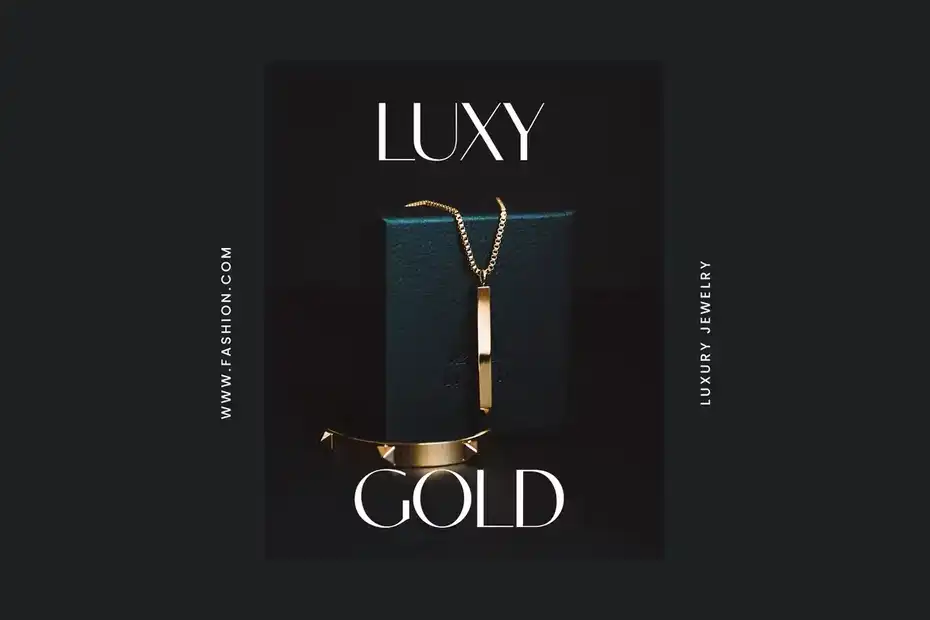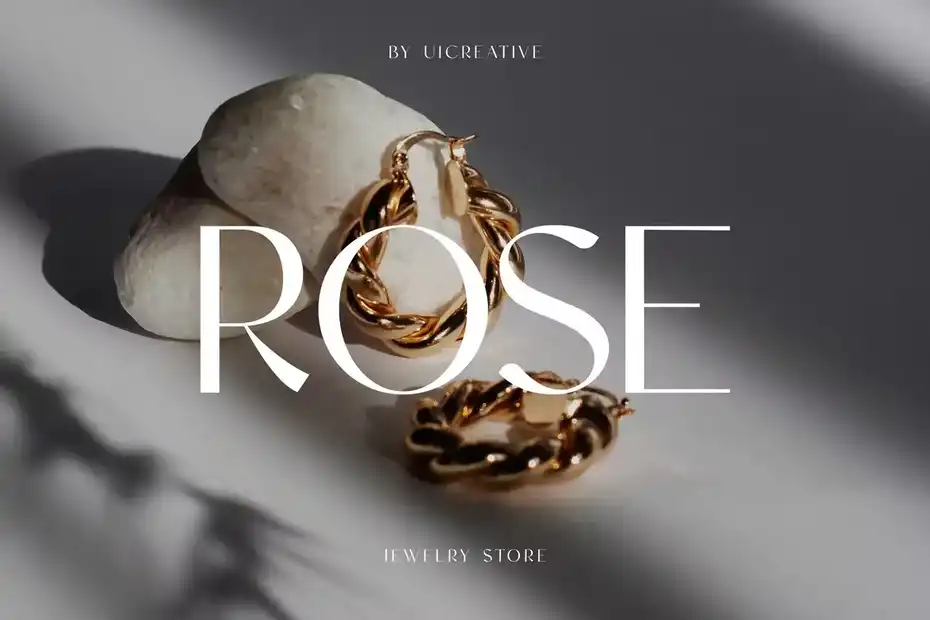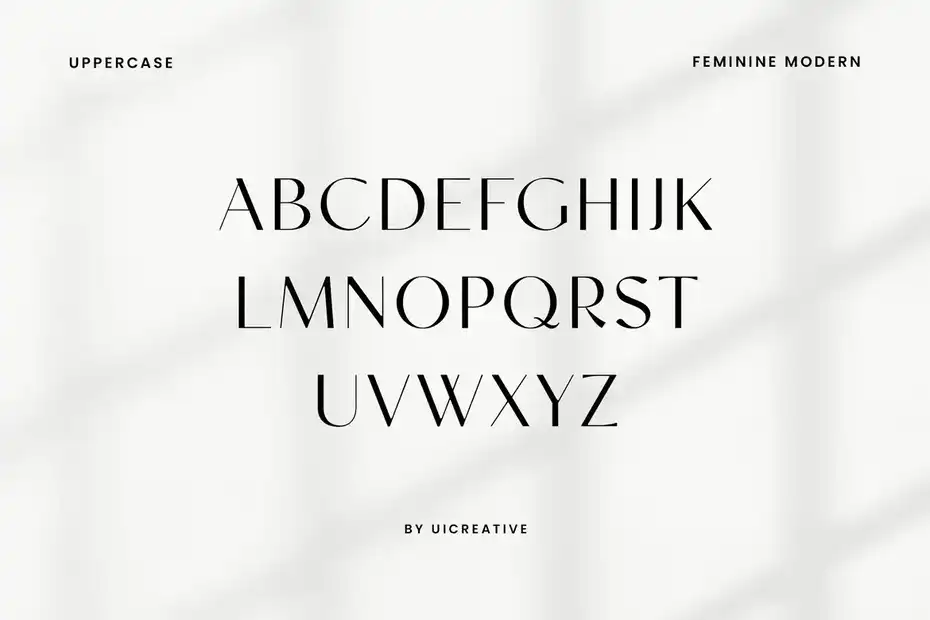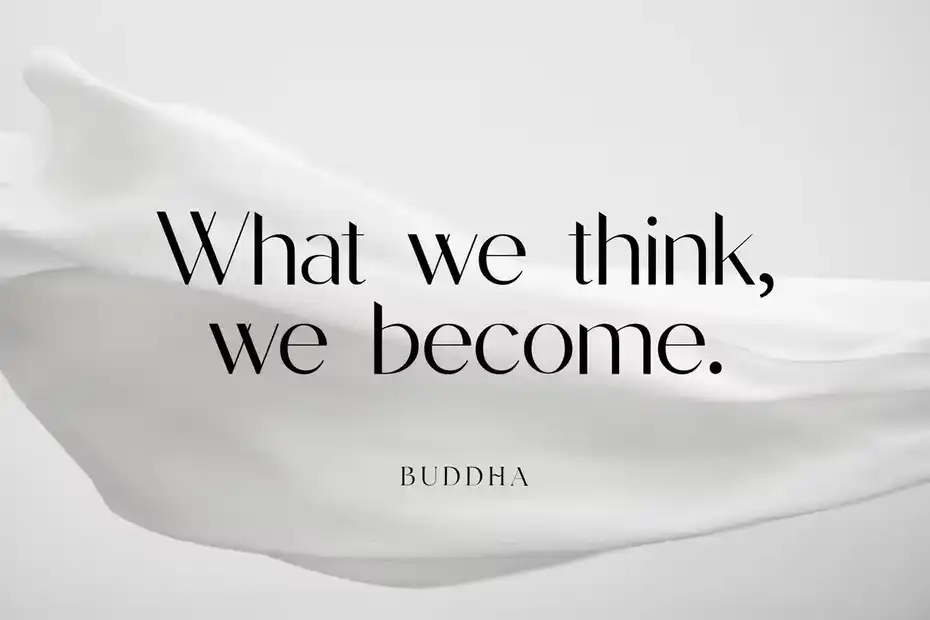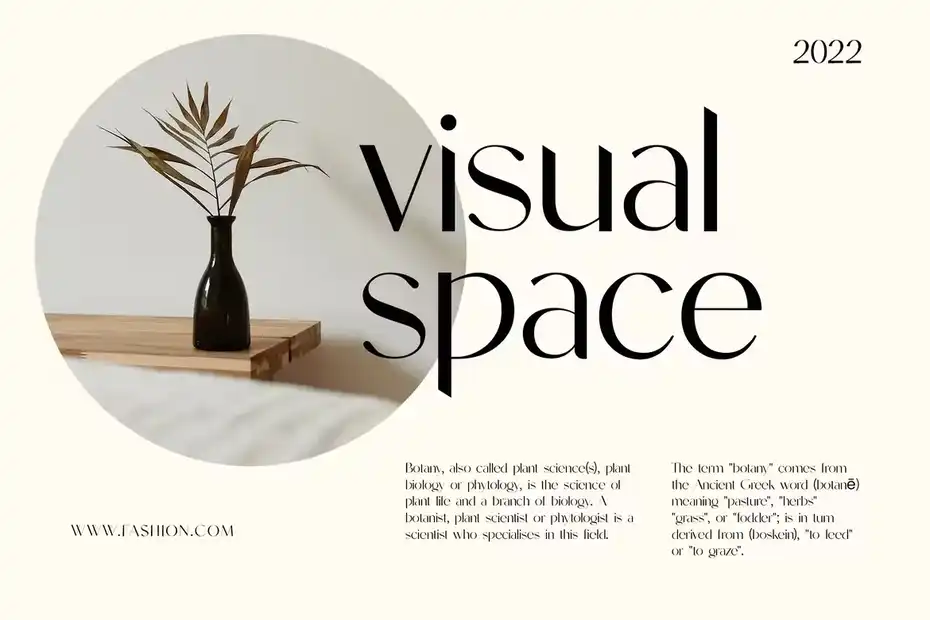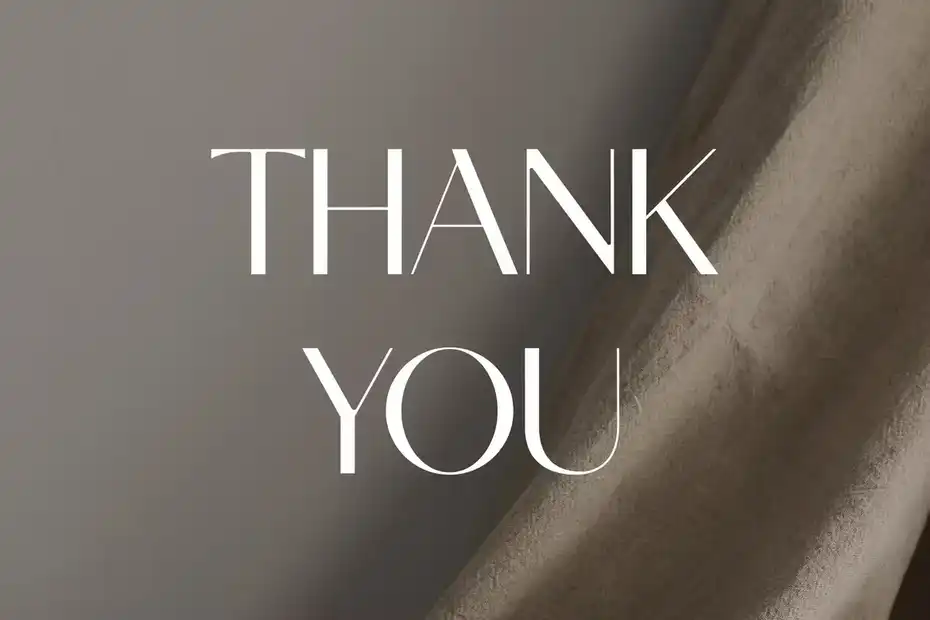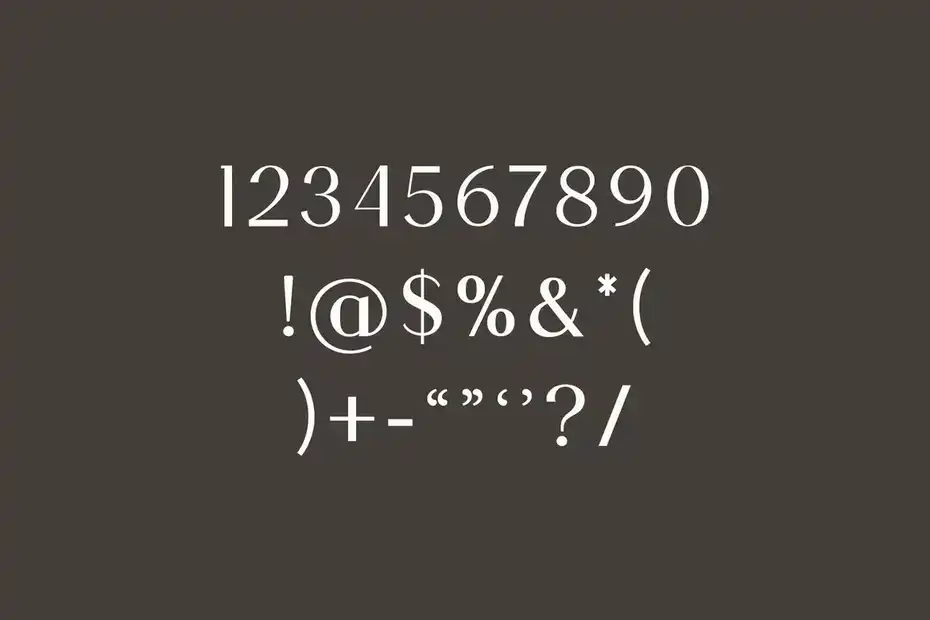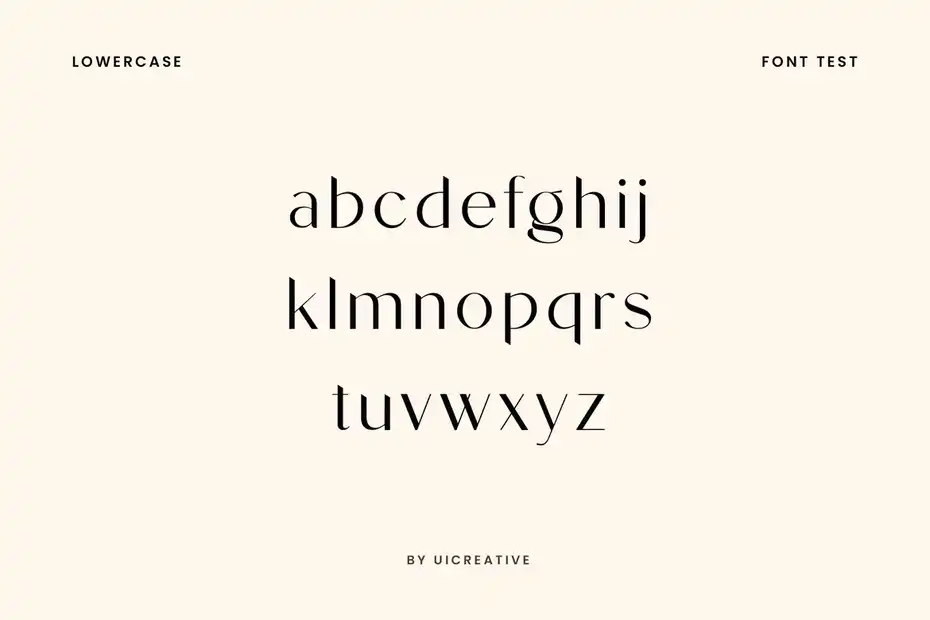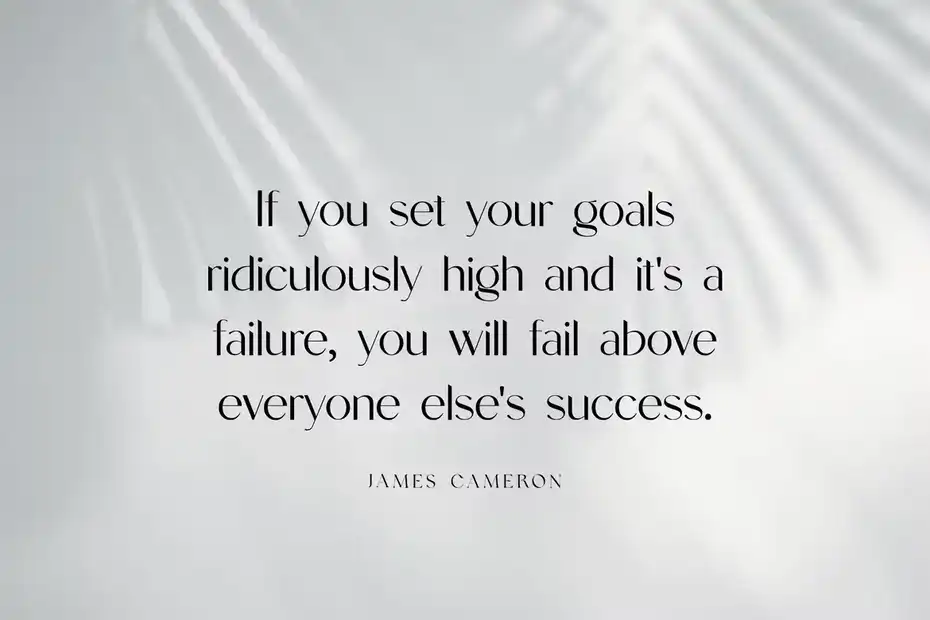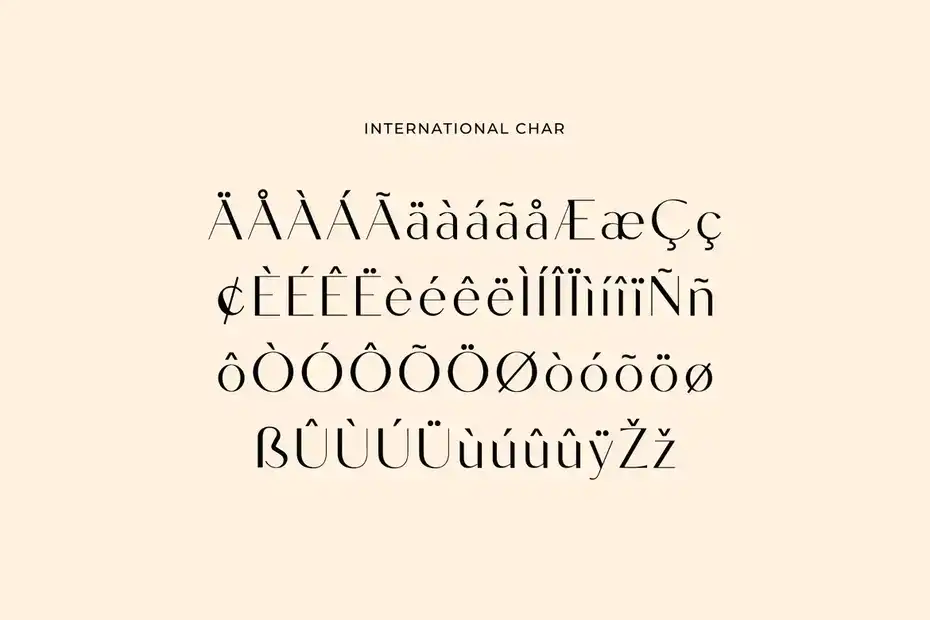
دانلود فونت انگلیسی Alona Ravigent Elegant Sans Serif Font
فونت انگلیسی Alona Ravigent Elegant Sans Serif Font : این فونت یک فونت مدرن Sans Serif است که برای پروژه های مختلف مانند: امضا، برندینگ، لوگو، عروسی، نقل قول تایپوگرافی، جلد مجلات یا کتاب، سربرگ وب سایت، لباس، طراحی بسته بندی و غیره مناسب میباشد.
فونت انگلیسی Alona Ravigent Elegant Sans Serif Font - 1
فونت انگلیسی Alona Ravigent Elegant Sans Serif Font - 3
فونت انگلیسی Alona Ravigent Elegant Sans Serif Font - 5
فونت انگلیسی Alona Ravigent Elegant Sans Serif Font - 7
فونت انگلیسی Alona Ravigent Elegant Sans Serif Font - 9
فونت انگلیسی Alona Ravigent Elegant Sans Serif Font - 11
فونت انگلیسی Alona Ravigent Elegant Sans Serif Font - 13
فونت انگلیسی Alona Ravigent Elegant Sans Serif Font - 15
فونت انگلیسی Alona Ravigent Elegant Sans Serif Font - 17
فونت انگلیسی Alona Ravigent Elegant Sans Serif Font - 19
فونت انگلیسی Alona Ravigent Elegant Sans Serif Font - 21
فونت انگلیسی Alona Ravigent Elegant Sans Serif Font - 23